印品雅宋简字体线条流畅顺滑,平整耐看,棱角柔滑,装饰角的圆滑处理,使整款字体看起来既不缺少正式感又能增添个性,字体浑厚有力十分耐看,整体庄重,结实,端正大气,适用于标题,封面等场景。
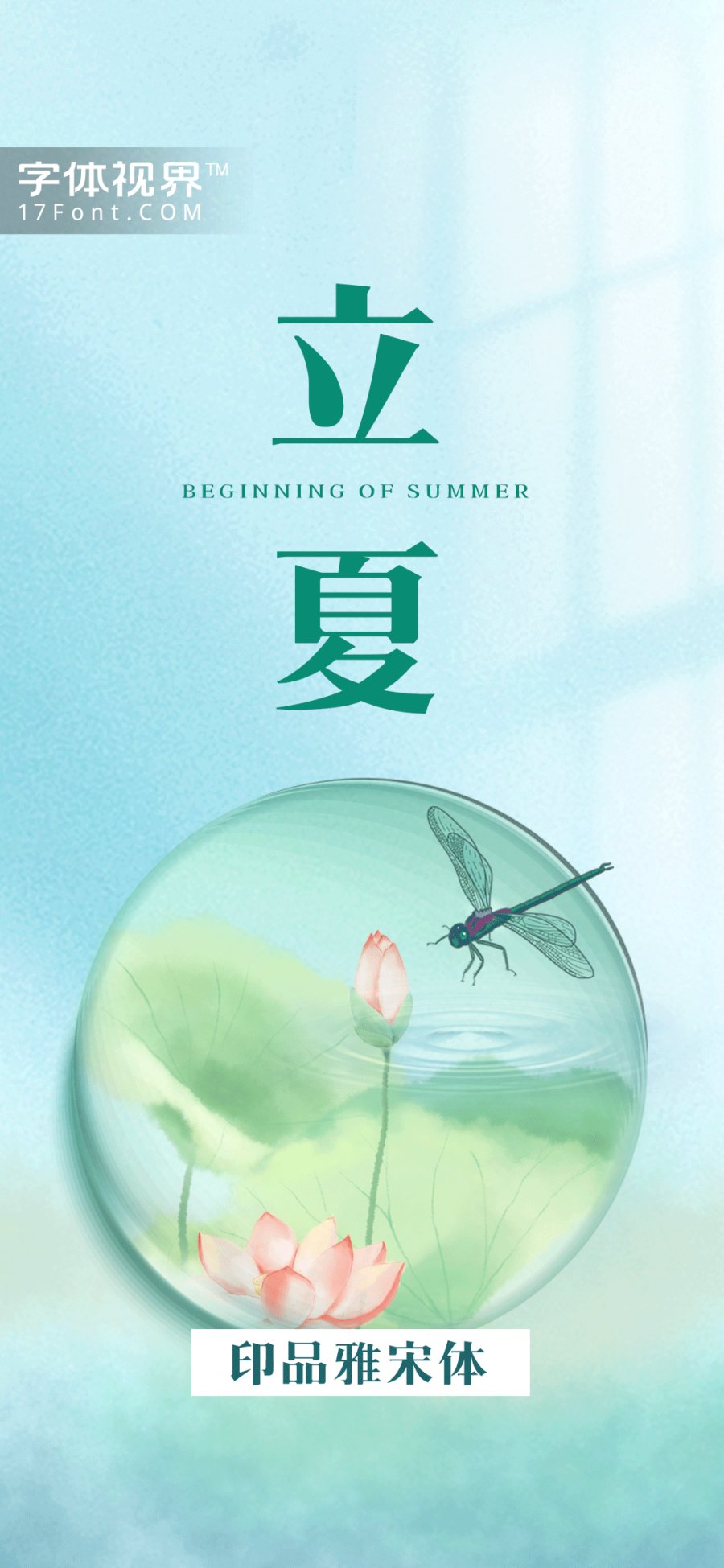
不觉春已逝, 转眼夏伊始。汉呈安景臣手书体来报道。
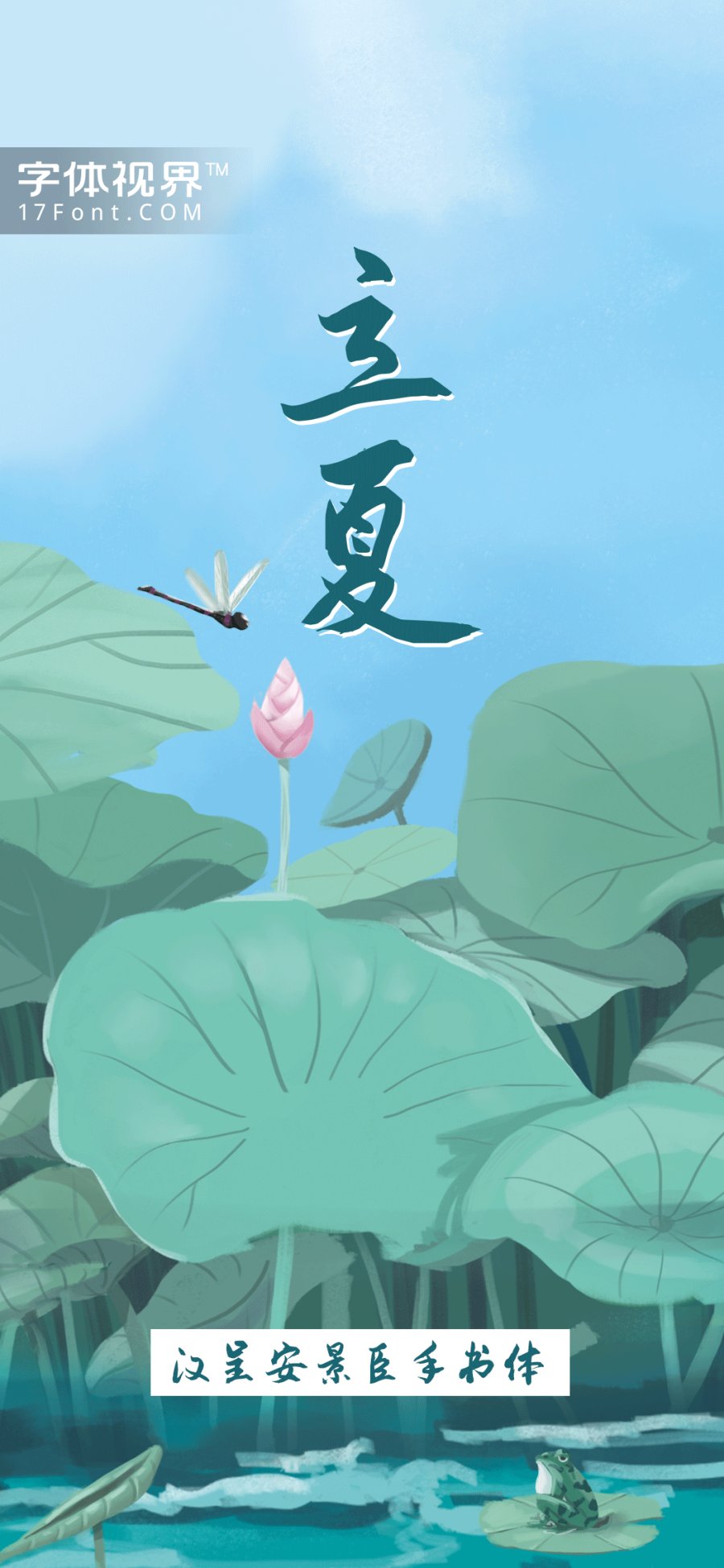
上首夏木体,简体中文约6763字,字体修长,起笔落笔圆角处理,呈现精巧的感觉。适用于搭配标志、广告标语、商业广告等高端属性。